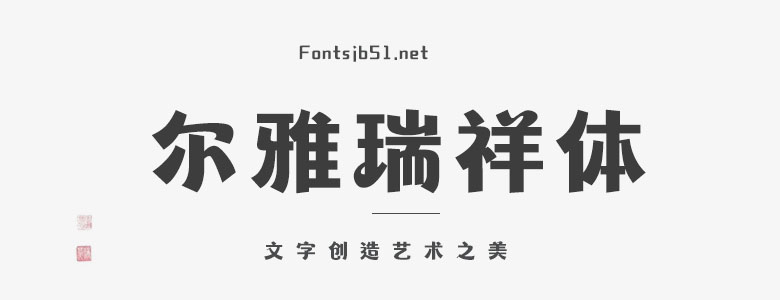
爾雅瑞祥體
爾雅瑞祥體是一款卡通可愛的創(chuàng)意時(shí)尚字體,適合應(yīng)用于藝術(shù)設(shè)計(jì)、平面宣傳設(shè)計(jì)、網(wǎng)頁設(shè)計(jì)、書法字體,海報(bào)設(shè)計(jì)等領(lǐng)域,歡迎喜歡這款字體的朋友下載收藏。